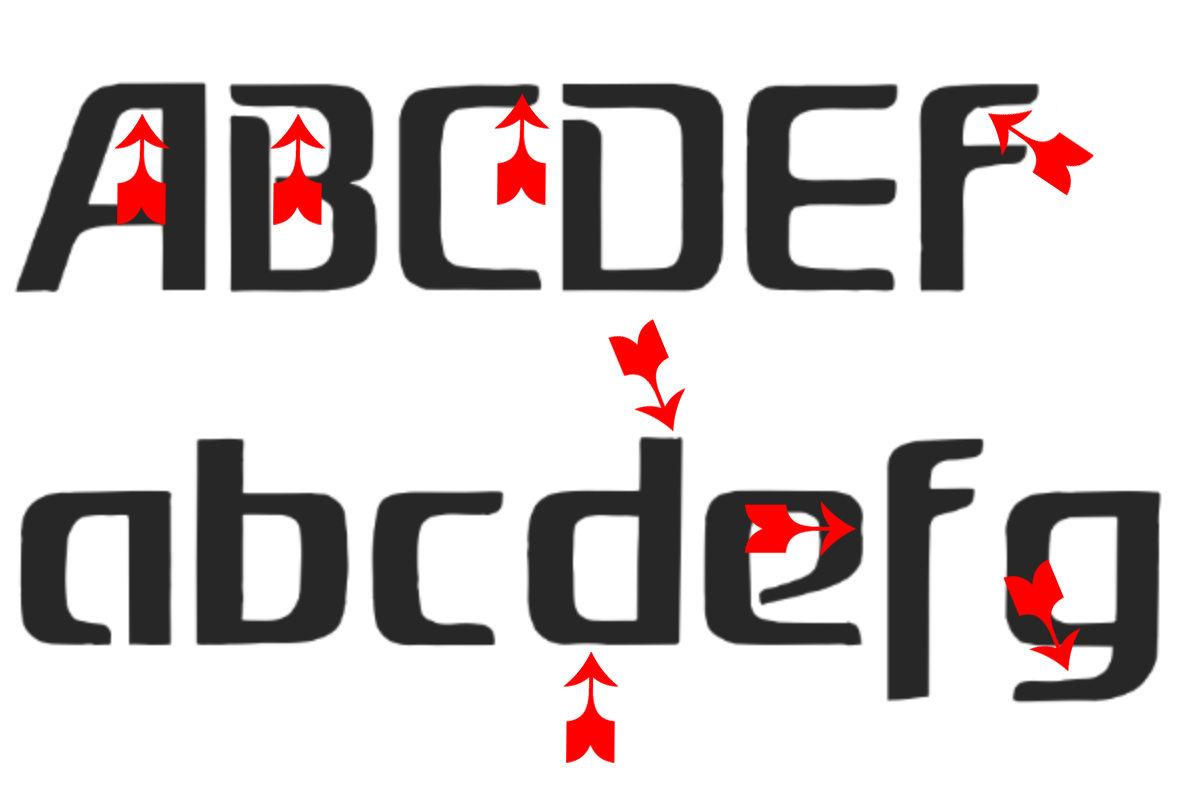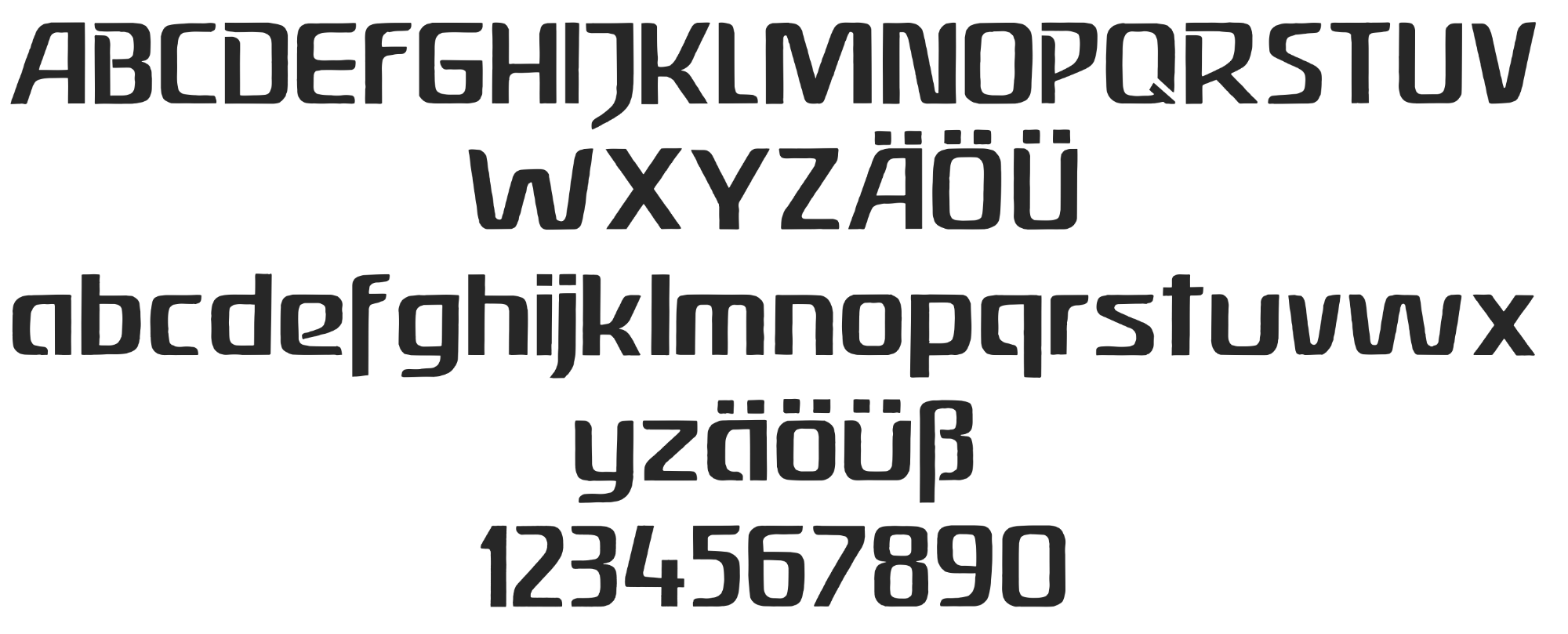
Schrift für ein Unternehmen mit anthroposophischer Ausrichtung
Mein Auftraggeber, ein Unternehmen mit anthroposophischer Ausrichtung, möchte sein Erscheinungsbild
modernisieren, dabei aber die bisherige "Hausschrift" unbedingt (!) beibehalten. Der Haken:
Der ehemalige Gestalter (vor vielen Jahren) ist unbekannt –
und niemand weiß, wie die Schrift heißt. Ich habe sie auch nirgends finden können.
Vielleicht kennt sie jemand? Für Hinweise bin ich dankbar.
wird es wohl custom sein.
Das vermute ich aufgrund der Unregelmäßigkeiten auch. Die Buchstaben sehen mir auch nicht so aus, als wären sie in einem Vektorprogramm erstellt worden, eher in einer Bildbearbeitungssoftware.
Wenn du den Kundennamen nennen könntest, könnte man sich besser auf die Suche machen. Als Teil seiner Erscheinungsbildes spräche ja nichts dagegen …
der Haken an der Sache ist weniger, daß der Schöpfer unbekannt ist, sondern eher, daß die Verantwortlichen anscheinend große dicke Demeter-Kartoffeln auf den Augen haben. Aber es könnte eine interessante Aufgabe sein, aus dieser Schriftidee etwas brauchbares zu machen …
Naja Weleda ist da eine große Marke aus dieser Richtung. Die Weleda Schrift sieht aber leicht anders aus. Ich könnte mir vorstellen das eine kleiner Marke sich hier inspirieren lassen wollte und dann wurde daraus ein Schuh.
Wie gesagt ich kenne die Schrift hier nicht, könnte mir hier aber die individuelle Umsetzung erklären.